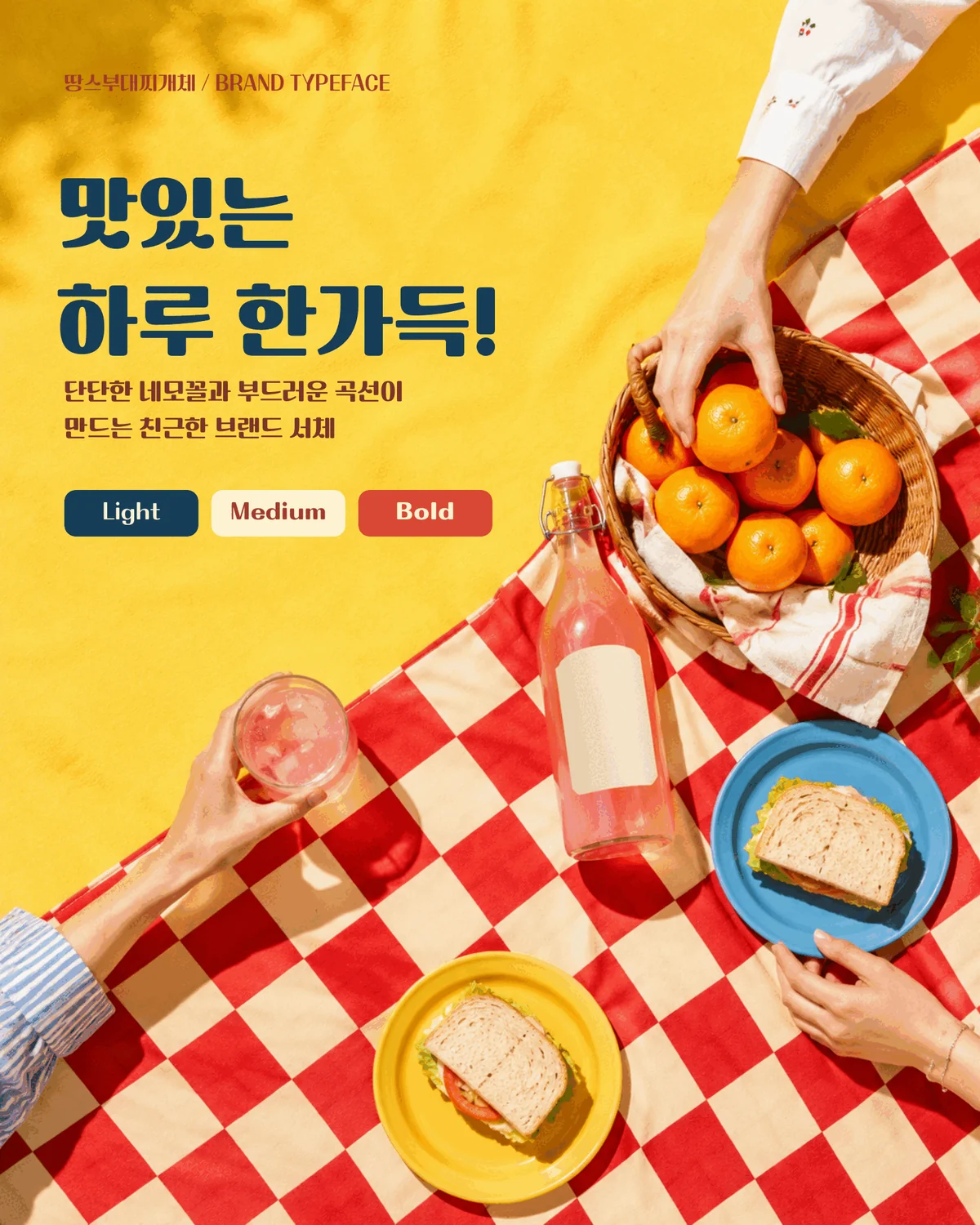
땅스부대찌개 — (주)티에스푸드에서 배포하는 무료 폰트입니다. 넓고 둥근 네모꼴 구조에 부드러운 곡선을 더한 단단하고 친근한 브랜드 서체
부대찌개 테이크아웃 전문점 땅스부대찌개를 운영하는 티에스푸드가 2023년에 내놓은 첫 브랜드 서체입니다. 만든 이유를 제작사가 직접 밝혔습니다. 편리하고 친근한 이미지를 서체에 담아 전달하고자 만들었다는 것입니다.
이름 때문에 손글씨를 떠올리기 쉽지만 실제로는 둥근 고딕입니다. 배포처 설명에 따르면 넓은 사각 모듈 구조를 기반으로 곡선 포인트를 써서 따뜻하고 유쾌한 인상을 전달하며, 넉넉한 3인분처럼 공간감을 최대화한 디자인입니다. 파일에서 재어 보면 낱자가 가로로 넓게 퍼져 있어 그 설명과 맞습니다. 부대찌개 아이콘을 딩벳으로 넣어 두기도 했습니다.
굵기는 Light와 Medium, Bold 세 가지라 제목과 부제목의 위계를 만들 수 있습니다. 메뉴판과 사이니지, 패키지처럼 음식점 환경을 겨냥한 서체입니다. 수정과 재배포가 허용되지만 회사명이나 로고 같은 BI와 CI 용도는 별도 조건 확인이 필요하니 그런 용도라면 미리 문의하세요.